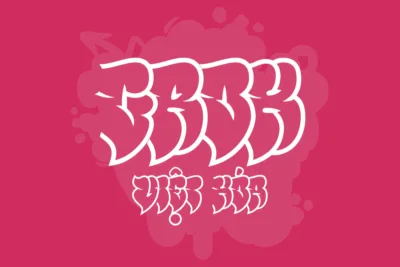
Bộ Typography Kỷ Yếu Set 4 mới nhất – Đẹp mắt
Kỷ yếu không chỉ là một cuốn sách ghi lại những kỷ niệm, mà còn là một bức tranh tươi đẹp của thời học sinh, với mỗi chi tiết được chăm chút kỹ lưỡng. Và giờ đây, Bộ Typography Kỷ Yếu Set 4 sẽ mang đến cho bạn nét đẹp mới, sôi động và đậm chất cá nhân, tạo nên một kỷ yếu độc đáo và đáng nhớ.